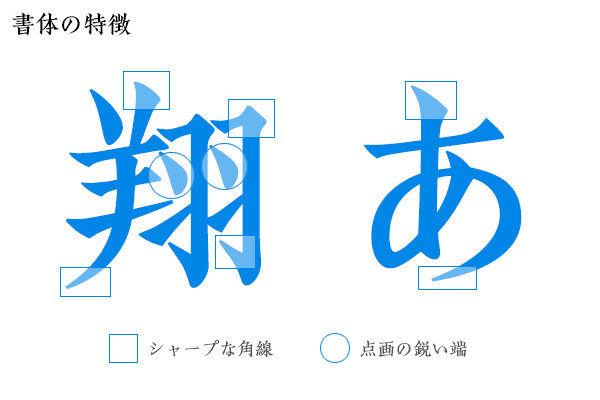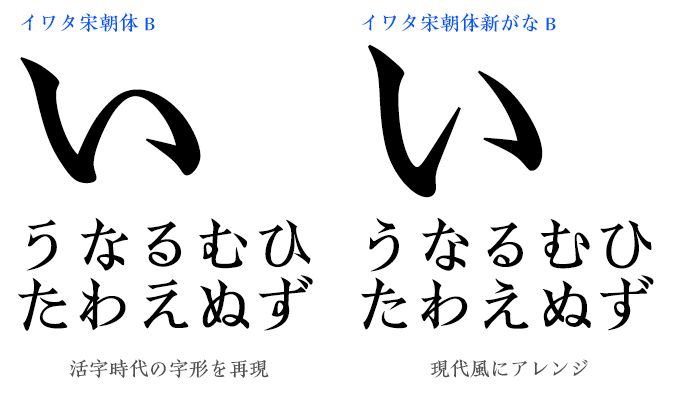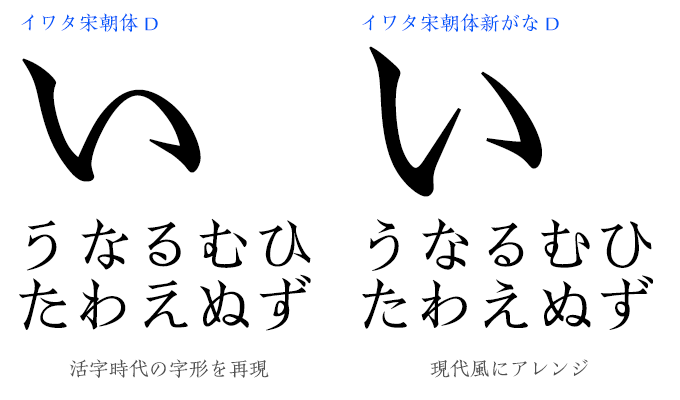
イワタ宋朝体
名刺・広告・書籍でタイトルから本文まで大活躍のイワタ宋朝体
イワタ宋朝体は、シャープな角線と点画の鋭い端が特徴の格調高い書体です。古風な形と現代的なアレンジも加えて待望の復刻を果たしました。
名刺や広告、書籍のタイトルから本文組みまで、明朝体とはまたひと味違う新しい感覚の組版が行えます。
イワタ宋朝体の魅力
中国の宋の時代、木版印刷に用いられる印刷書体として成立したのが宋朝体です。当時は、日本でも活字としても多いに活躍した書体です。
日本では現在、本文用書体としては明朝体を用いることが多いですが、中国では現在も公文書等の格式を重んじる場合や、書籍の刊行などに宋朝体が広く使用されています。
イワタ宋朝体のもとになっているのは、かつて金属活字を製作していた岩田母型の方宋体活字。シャープな角線と点画の鋭い端が特徴の伝統書体そのままに、新たにJISに準拠しデジタル化した書体です。
筆書系書体の中でも、凜とした清涼感さえ感じさせる宋朝体。イワタの宋朝体を季節のご挨拶などに使われてはいかがでしょうか。
かな違いの2系統 & 3種類のウェイト
イワタ宋朝体のラインナップは、活字時代の漢字と仮名を再現した「イワタ宋朝体」と、仮名デザインを現代風にアレンジした「イワタ宋朝体新がな」の2系統が用意されています。
「イワタ宋朝体」「イワタ宋朝体新がな」それぞれにM/D/Bの3ウェイトが用意された、合計6書体のラインナップです。
M/D/Bウェイトそれぞれに、通常と新がな2系統のかなデザインというラインナップです。